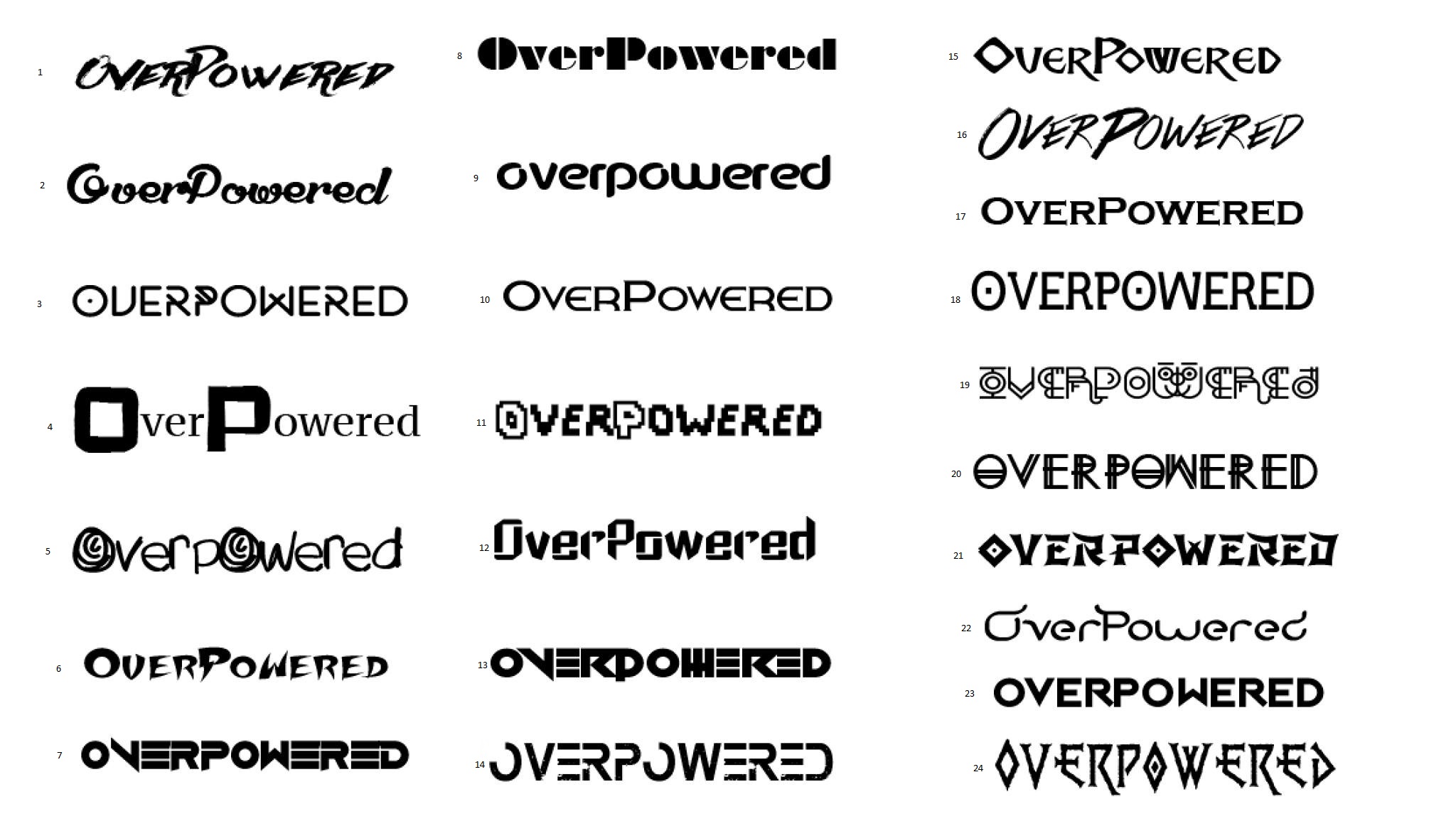
Hei, kan dere komme med deres synspunkter for hvilken font dere liker best?
Fonten skal på et gaming produkt.
Kan stemme på nummer 8 siden den ligner mest på et tyggegummi merke jeg ikke husker navnet på. For å være ærlig ser det rett og slett ut som du har hentet 24 tilfeldige fonter fra dafont, og valgt et navn som kunne ha vært på olabilen til en seks åring.
Orbit?
9